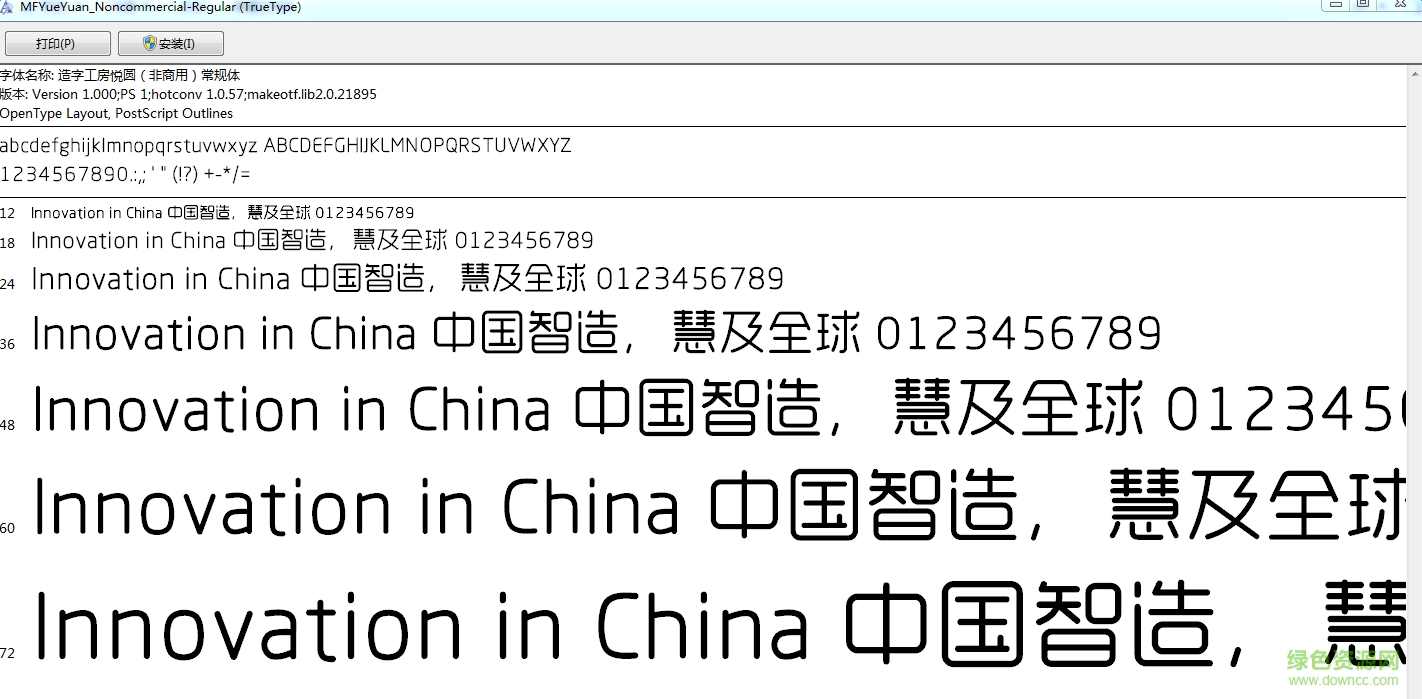
造字工房悅圓體字體
造字工房悅圓體是一款造字工房類圓形風(fēng)格字體軟件,悅圓體給人非常圓潤清爽的感覺,適用于品牌標(biāo)題設(shè)計(jì)與推廣,也深受廣大書法家的喜愛,還有更多好看字體盡情期待,歡迎到綠色資源網(wǎng)下載體驗(yàn)!
造字工房悅圓常規(guī)字體為圓體字形,結(jié)構(gòu)秉承悅黑系列,筆畫風(fēng)格簡(jiǎn)潔,柔美優(yōu)雅。具有較大范圍的應(yīng)用空間。適用于高端時(shí)尚品牌產(chǎn)品的形象設(shè)計(jì)與推廣。